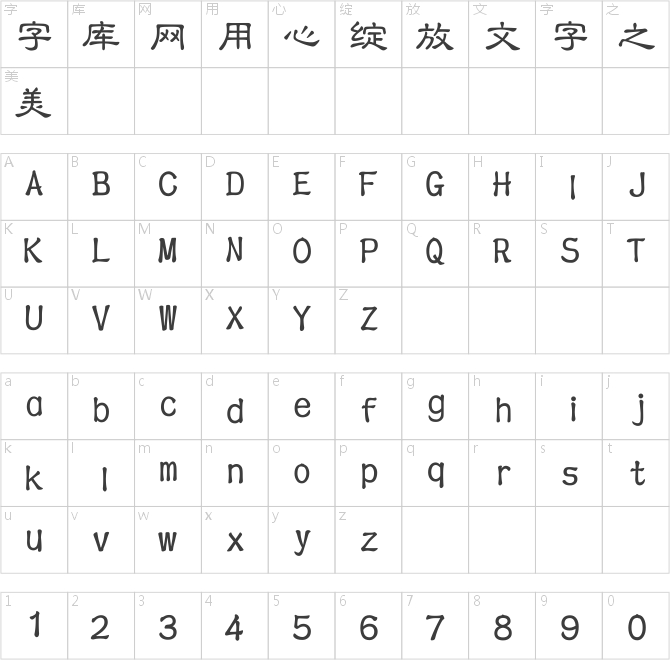
文鼎中粗隸簡繁 詳情頁
字體名稱: 文鼎中粗隸簡繁
作者版權: 文鼎字庫
文鼎中粗隸簡繁
文鼎公司的中粗隸只有big5繁體版本的沒有gb2312簡體版本的,故本人將『文鼎中隸簡』進行了加粗和輪廓線合并并并入『文鼎中粗隸big5』而形成了簡易的『文鼎中粗隸簡繁』原生向上兼容新版win10
20220220更新:添加日語當用漢字。一共16718個漢字。